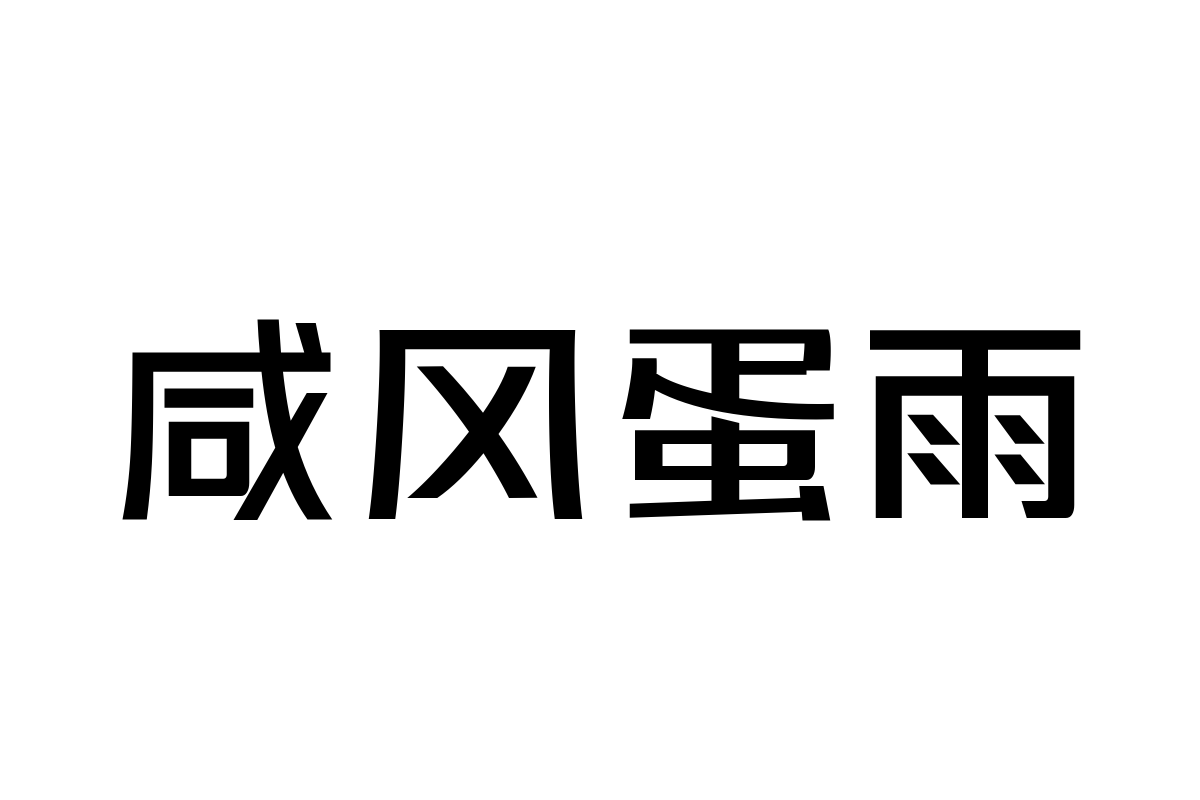
三极力量酷黑字体是一种具有现代感和科技感的无衬线字体,它以其简洁、清晰和易读的特点而受到广泛欢迎。这种字体的设计灵感来源于现代电子设备的设计元素,如屏幕、按钮和图标等,因此它通常被用于需要强调速度、效率和精确性的场合。
三极力量酷黑字体的特点是:
1. 无衬线设计:这种字体没有额外的线条来装饰每个字符,这使得它在视觉上更加简洁和清晰。
2. 易于阅读:由于它的无衬线特性,这种字体非常适合用于需要快速阅读的场合,如网页、广告牌和产品包装等。
3. 现代感:三极力量酷黑字体的设计灵感来自于现代电子设备的元素,这使得它在视觉上呈现出一种时尚和现代的感觉。
4. 可扩展性:这种字体可以很容易地与其他字体混合使用,以创造出各种独特的视觉效果。
5. 适用于多种场景:无论是在网页、广告牌还是产品包装上,三极力量酷黑字体都能提供一种清晰、现代的视觉效果。